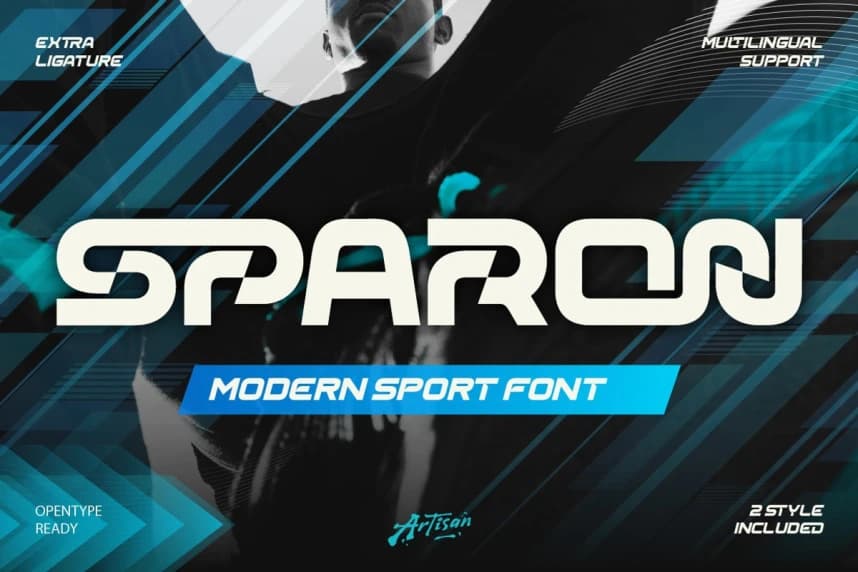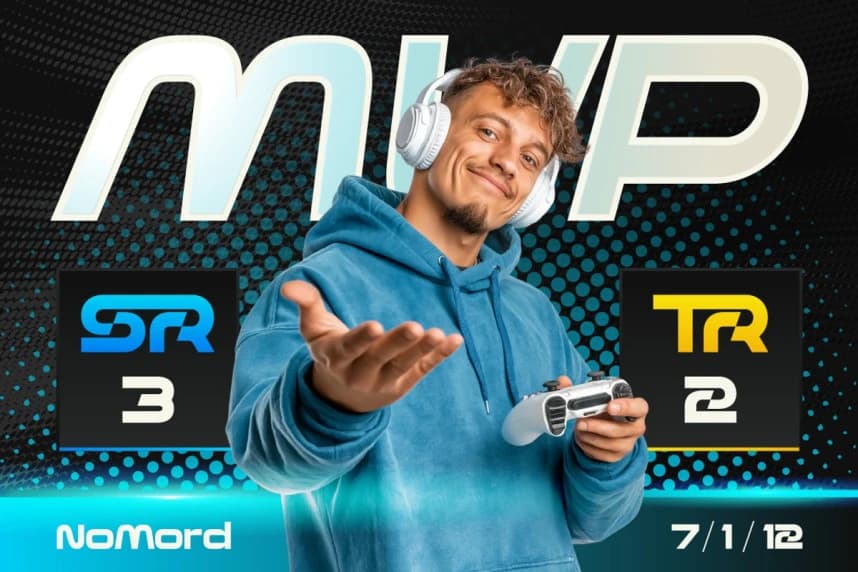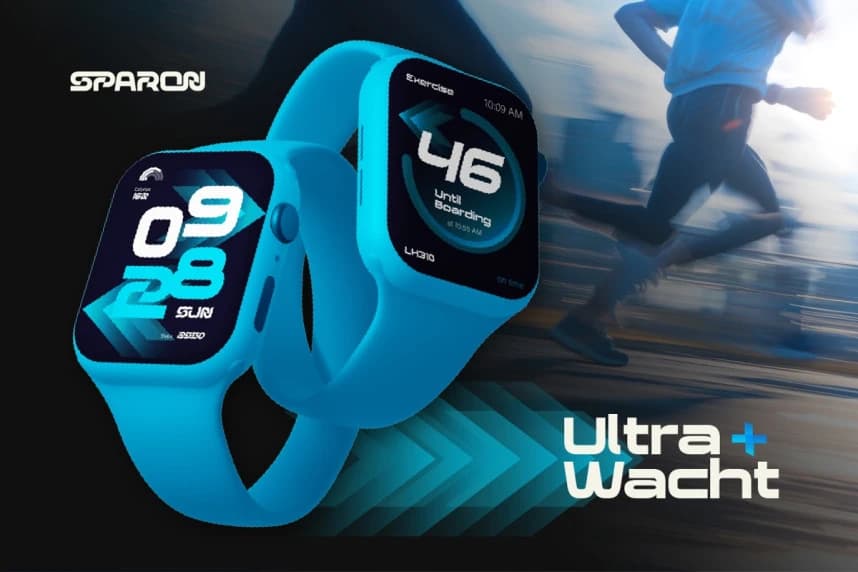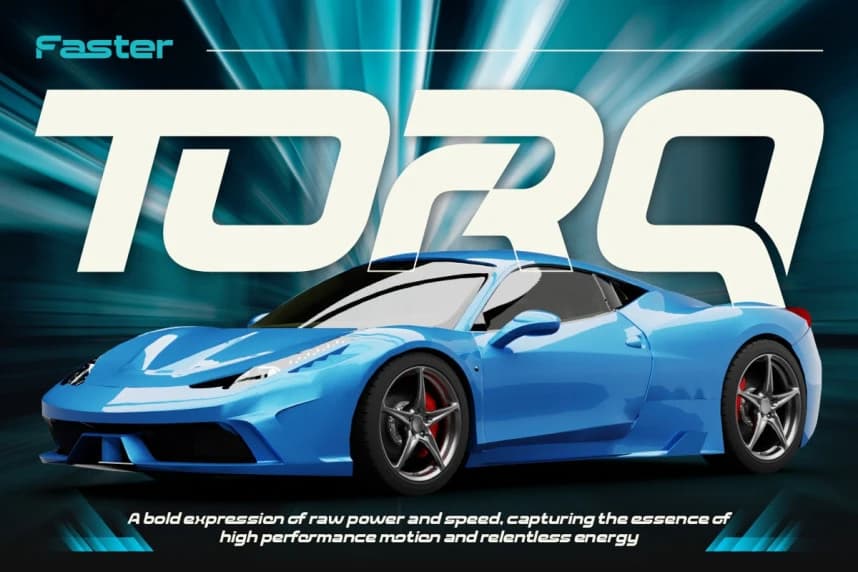
Sparon Font
Sparon Font, hızın, gücün ve yüksek performans enerjisinin ruhunu yakalamak için tasarlanmış cesur ve dinamik bir modern spor fontudur. Keskin hatlarıyla, fütüristik eğrileriyle ve agresif stiliyle Sparon, hızlı, güçlü ve etkileyici hissettirmesi gereken tasarımlar için mükemmeldir.
Sparon Font, hızı, gücü ve yüksek performans enerjisini yakalamak için tasarlanmış cesur ve dinamik bir modern spor fontudur. Keskin hatları, fütüristik eğrileri ve agresif tarzıyla Sparon, hızlı, güçlü ve etkileyici his veren tasarımlar için idealdir.